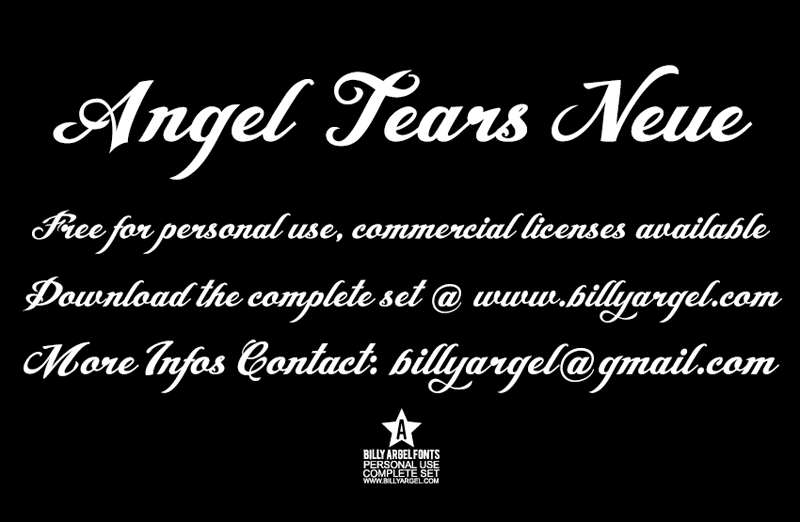
Angel Tears Neue Font – Download Grátis
A fonte ‘Angel Tears Neue’ é uma mão-dura elegante criada pelo designer Hamilton, perfeitamente adequada para escrita artística ou personalização de logotipos. Esta fonte é ideal para quem deseja dar um toque especial a mensagens individuais e aniversários, dando-lhes um aspecto único e encantador. A natureza handwritten deste tipo confere uma textura única e suave ao texto, tornando-a perfeita para uso pessoal ou em pequenas tarefas comerciais. O designer disponibiliza a fonte de forma gratuita para uso pessoal, com informações adicionais e licenças completas disponíveis no site billyargel.com. Não hesite em explorar ainda mais o trabalho do designer Hamilton visitando sua página oficial: www.billyargel.com.